Tema desain ramadhan atau islami tidak hanya menggunakan gambar atau dekorasi islami tetapi juga gaya tipografi Arabic. Style tipografi Arabic akan memiliki sentuhan huruf tradisional, gaya kaligrafi dan dekorasi huruf Arab. Style font Arabic bisa digunakan untuk desain tema ramadhan, branding logo makanan Arab hingga logo fashion muslim.
Gaya tipografi Arabic akan memiliki bentuk huruf seperti huruf Arab, dekorasi titik-titik, hingga sentuhan garis lengkungan tradisional. Penggunaan font Arabic yang unik untuk merepresentasikan tema islami atau ramadhan, kebanyakan cocok untuk desain logo atau font display poster.
TIPOGRAFI DESAIN RAMADHAN
Gaya tipografi yang khas untuk desain ramadhan biasanya memiliki style huruf elegan dan sentuhan huruf Arabic. Style font Arabic akan merepresentasikan tema ramadhan dan islami dengan baik. Pilih font bergaya Arabic yang mudah dibaca dan memiliki gaya huruf yang menarik.
Menciptakan Kesan Elegan dan Tenang
Tipografi untuk desain ramadhan tidak hanya menggunakan font dengan aksen huruf Arab tetapi juga style font biasa. Untuk tema ramadhan, tipografi yang cocok biasanya menggunakan font elegan. Jenis font script dan serif elegan akan menciptakan desain ramadhan dengan kesan elegan dan tenang. Font elegan bisa menciptakan desain ramadhan bertema mewah atau ekslusif.
Memiliki Kesan Islami
Tentunya gaya huruf seperti kaligrafi tradisional atau modern yang bernuansa islami akan relevan. Desain tema ramadhan sering juga menggunakan tipografi bergaya kaligrafi dan yang memiliki bentuk seperti huruf Arab. Gaya huruf tersebut akan efektif merepresentasikan desain bertema islami.
Mudah Dibaca
Desain bertema ramadhan juga sebaiknya menggunakan font sederhana yang mudah dibaca. Font dengan aksen huruf Arab terkadang memiliki keterbacaan yang buruk pada ukuran kecil. Untuk teks berukuran kecil, gunakan style font sederhana seperti sans serif atau serif agar mudah dibaca.
Unik dan Memiliki Detail yang Khas
Tipografi bertema islami dan ramadhan kerap memiliki bentuk huruf Arab yang unik serta detail tipografi yang khas. Banyak gaya tipografinya yang memiliki dekorasi titik-titik pada beberapa jenis font arabic. Sentuhan garis kaligrafi tradisional dan modern juga menjadi detail tipografi ramadhan yang unik.
REKOMENDASI FONT ARABIC YANG MENARIK
Desain grafis yang bertema islami atau ramadhan tentunya harus menggunakan gaya tipografi yang relevan. Font dengan style Arabic akan menciptakan nuansa islami yang relevan dan mudah dikenali. Gaya tipografi dengan sentuhan huruf arabis dan gaya kaligrafi akan relevan untuk berbagai tema desain islami.
Khodijah
Font bergaya seperti huruf Arabic ini memiliki huruf bersambung tetapi tidak terlalu rapat sehingga memiliki keterbacaan yang baik. Sentuhan huruf klasik alami kaligrafi Arab ini dapat menciptakan nuansa tradisional, klasik dan tampilan menarik. Bentuk hurufnya ramping, estetis, dan memiliki garis halus yang bersih dan lancip.
Penggunaan font khodijah yang elegan ini bisa menciptakan desain yang tenang dan mewah. Untuk branding produk yang berkualitas tinggi dan premium font ini akan cocok. Misalnya untuk logo parfum Arab, brand kurma hingga fashion Muslim yang mewah.
Shaumy
Tipografi pada font tersebut mengkombinasikan huruf alphabet seperti tulisan tangan dengan huruf Arabic. Dekorasi vokal arabic pada huruf menciptakan tampilan yang unik. Gaya font tersebut tampil playful dan menyenangkan, cocok untuk branding brand yang ramah.
Contohnya untuk desain branding bisnis makanan yang bernuansa islami dan halal akan mudah dikenali. Meski berkesan menyenangkan font tersebut masih memiliki nuansa huruf klasik dan religius. Gunakan untuk logo restoran atau buku cerita islami sehingga bisa merepresentasikan kesan ramah dan menyenangkan.
Ketupat Ramadhan
Style huruf dalam font ini lebih tebal dan memiliki lengkungan gaya tradisional dengan sentuhan modern. Dekorasi ornamen titik-titik, ujung yang agak panjang, serta lengkungan tradisional menciptakan nuansa klasik. Tampilan font yang unik tidak bisa digunakan pada ukuran yang kecil karena bisa sulit dibaca.
Gunakan style font Arabic ini untuk menarik perhatian pada desain logo, desain poster, kemasan maupun konten sebagai headline. Font tersebut akan membuat pesan utama mudah menarik perhatian dan menciptakan fokus utama. Kamu dapat menemukan font ini pada dafont namun perhatikan lisensi penggunaannya.
Bismillah
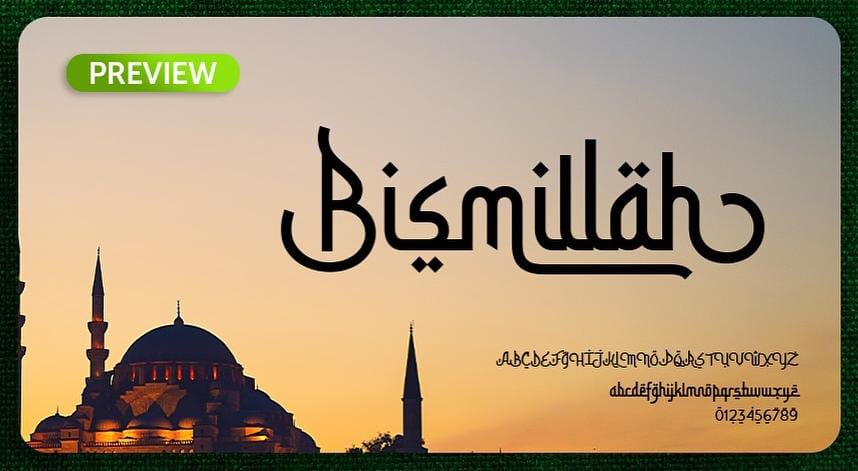
Style font Arabic untuk tema desain ramadhan dan islami sering memiliki huruf bersambung dan gaya hurufnya seperti huruf Arab. Font ini juga memiliki huruf bersambung dan bentuk huruf seperti huruf arab dengan dekorasi titik-titik yang khas. Gaya tipografi font ini tampil seperti kaligrafi Arab modern dengan bentuk huruf yang artistik dan khas.
Jenis font Arabic ini termasuk font display sehingga cocok digunakan sebagai headline dan mampu menciptakan makna yang simbolis. Font akan cocok digunakan sebagai logo yang menggabungkan budaya dan desain kontemporer. Contohnya desain kemasan produk premium, signage atau desain poster bertema ramadhan.
Gaya font Arabic memiliki bentuk huruf seperti huruf Arab dengan dekorasi titik-titik serta garis melengkung tradisional. Tipografi Arabic akan merepresentasikan desain bertema islami atau ramadhan. Ada banyak variasi gaya huruf arabic yang mendetail dan khas yang bisa digunakan untuk berbagai desain.